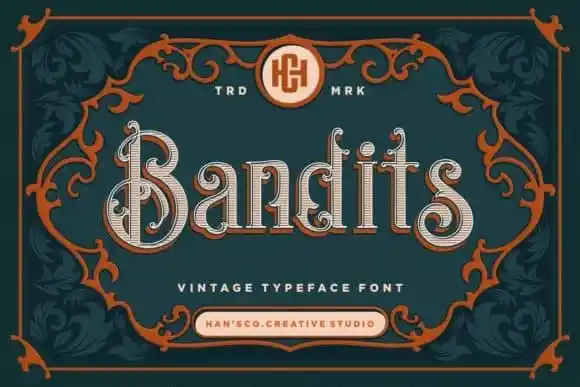
Bandits Display Font – Download Grátis
Bandits Display Font é uma fonte de exibição vintage que evoca a icônica aparência do trompe l’oeil, trazendo à vida o estilo das artes decorativas barrocas com ornamentos extremamente elaborados. Com sua elegância sofisticada e sutileza única, essa fonte se destaca como uma escolha perfeita para criar um ar de luxo em qualquer projeto design. Seja para inspirar designs inspiradores a partir dos logotipos vintage ou para projetos vintage que exigem um toque atraente, como o branding, os logotipos vintage, as frases e até mesmo estampas de camisetas, essa fonte é perfeita. Não hesite em experimentar Bandits Display Font para adicionar uma pitada única de luxo e elegância à sua próxima criação gráfica.